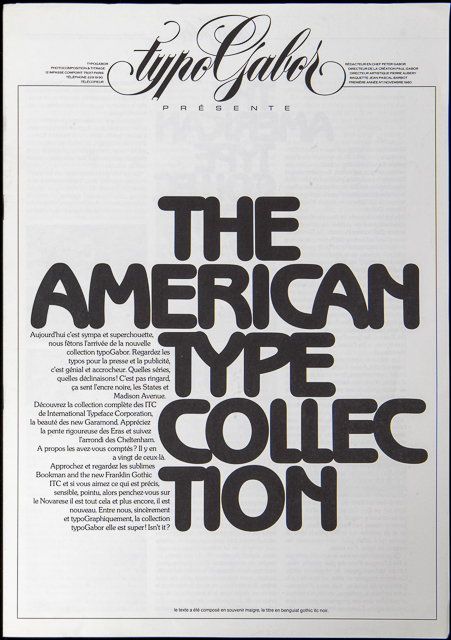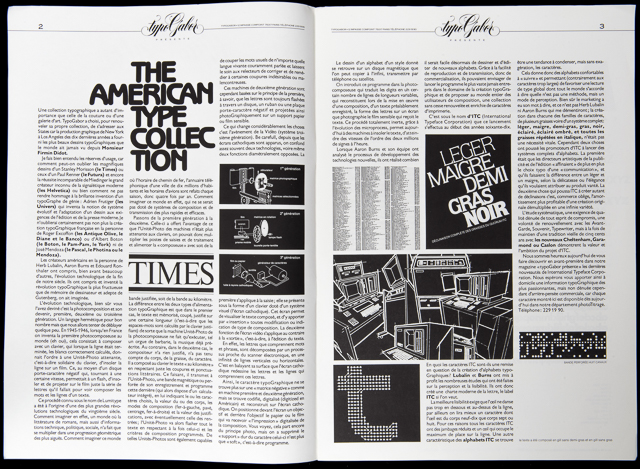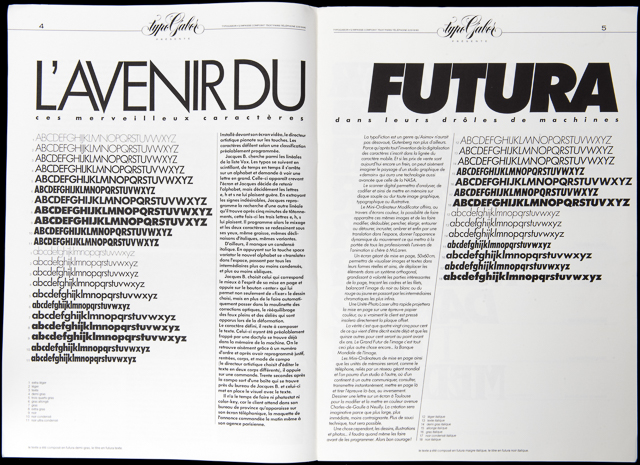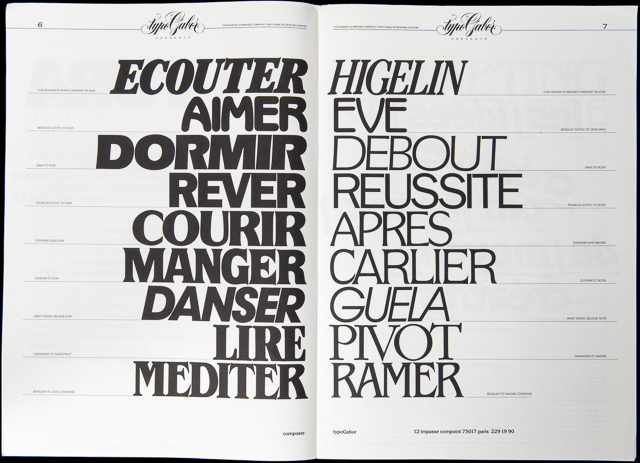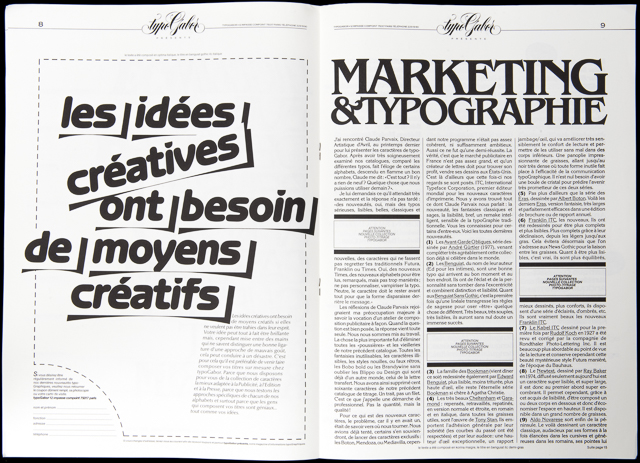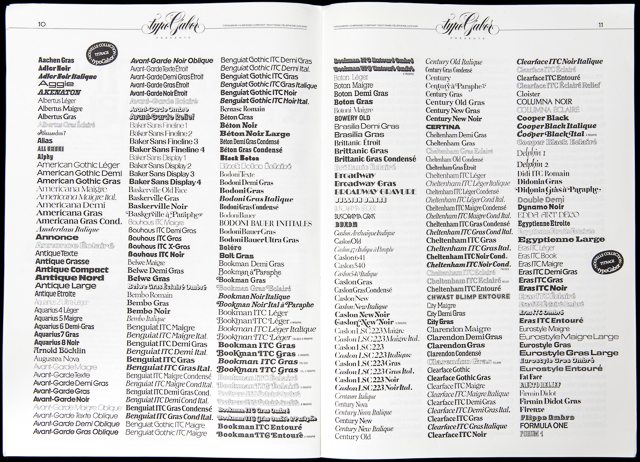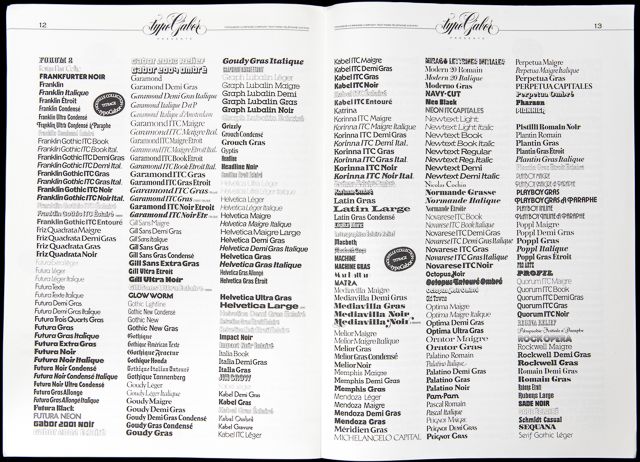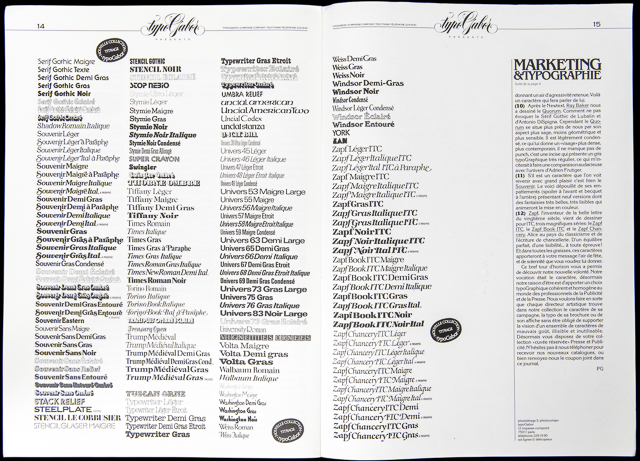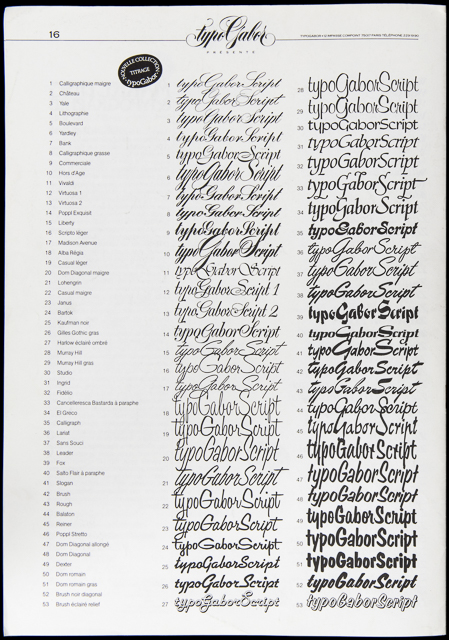
L’histoire des magazines typoGabor | N°1 American Type Collection
Même si certaines manifestations graphiques sont en germe dès 1968, typoGabor est fondée en 1973 par Paul et Peter Gabor. L’activité de la société est double : atelier de création graphique autour des clients historiques de Paul Gabor et société de services typographiques sous l’égide de Peter Gabor.
Les premières années de typoGabor sont rythmées par le fonctionnement coûteux et limité des Diatronic de Berthold. Tant et si bien qu’à la fin des années 1970, la continuité d’exploitation semble compromise. C’est à la faveur d’une annonce dans la revue CARACTÈRE que Peter Gabor découvre l’AlphaType. Il y voit l’amorce d’une révolution du digital. Ce sera son ami (depuis) Raymond Aubry, chef d’Atelier de Graphiservice à Bruxelles qui achèvera de le convaincre. Un système de composition américain venant de Chicago, qui pour la première fois, propose non plus d’acheter mais de louer (prix dérisoire) des polices de caractères, ce qui porte l’offre et la diversité typographiques à un niveau inédit : 1 000 polices contre 80 sur Diatronic auxquels s’ajoutent 16 polices supplémentaires tous les mois. « typoGabor présente » naît en 1980 de deux constats. Il ne s’agit plus de faire de la Pub pour une entreprise, mais d’informer et d’éduquer un marché. La Publicité. Un marché où s’affrontaient une trentaine de concurrents proposant tous à peu près les mêmes services (24/24, coursiers, catalogues de calibrage gratuits et qualité de composition supérieure à celle de l’édition ou de la Presse). typoGabor connaît alors le succès. Les Directeurs Artistiques affluent et les commandes doublent de volume en l’espace de 2 ans. Mais la formule marketing du magazine ne plaisait plus à Peter Gabor. Il y préféra une formule nouvelle autorisant toutes les expérimentations typographiques. Le magazine littéraire de typoGabor était né. Plusieurs directeurs artistiques vont se succéder dans les cuisines typographiques de la maison Gabor. Bill Butt, Jérôme Binda, Philippe Duriez et pour finir Paul Gabor qui revient en 89 par une magistrale œuvre consacré aux Droits de l’Homme. L’Âge d’Homme.
L’expérience de la photocomposition fut de courte durée. Le Postscript arrive sous la forme commercialisée d’Adobe Type Manager et tous les prestataires de composition perdent 50 clients par jour à partir de 1990. Peter Gabor tenta encore d’adapter son entreprise en devenant le premier compositeur qui a basculé la totalité de son fonds sur Macintosh. Mais les dettes s’accumulant et victime d’un administrateur judiciaire peu scrupuleux, il finit par baisser les bras, non sans avoir personnellement créé 4 polices de caractères pour le Journal Libération en 1994.
Une aventure de vie passée à promouvoir la diversité et la qualité de composition, parce que comme l’aimait à rappeler son père Paul, d’après une phrase de Jean Cocteau : «Le style n’est pas une danse mais une démarche».
Magazine «typoGabor présente» de novembre 1980 où il est question du lancement de la collection digitale des caractères de photocomposition de typoGabor. Technologie Alphatype.
• Si vous cliquez sur cette page, vous pourrez lire mes prévisions en bas de la deuxième colonne sur l’avenir du monde numérique tel que je l’imaginais. De fait la seule chose que je n’avais pas prévu tient en deux mots: marketing de masse. Le Mass Market a démocratisé les outils, à un point inimaginable à ce moment précis de l’histoire des technologies. Il faut savoir que les machines Alphatype que nous avions fait venir de Chicago coûtaient au bas mots environ 1,2 millions de FF. ce qui équivaut à un système de composition de texte à 163.000 €uros. C’est du lourd comme dirait Fabrice Luchini.